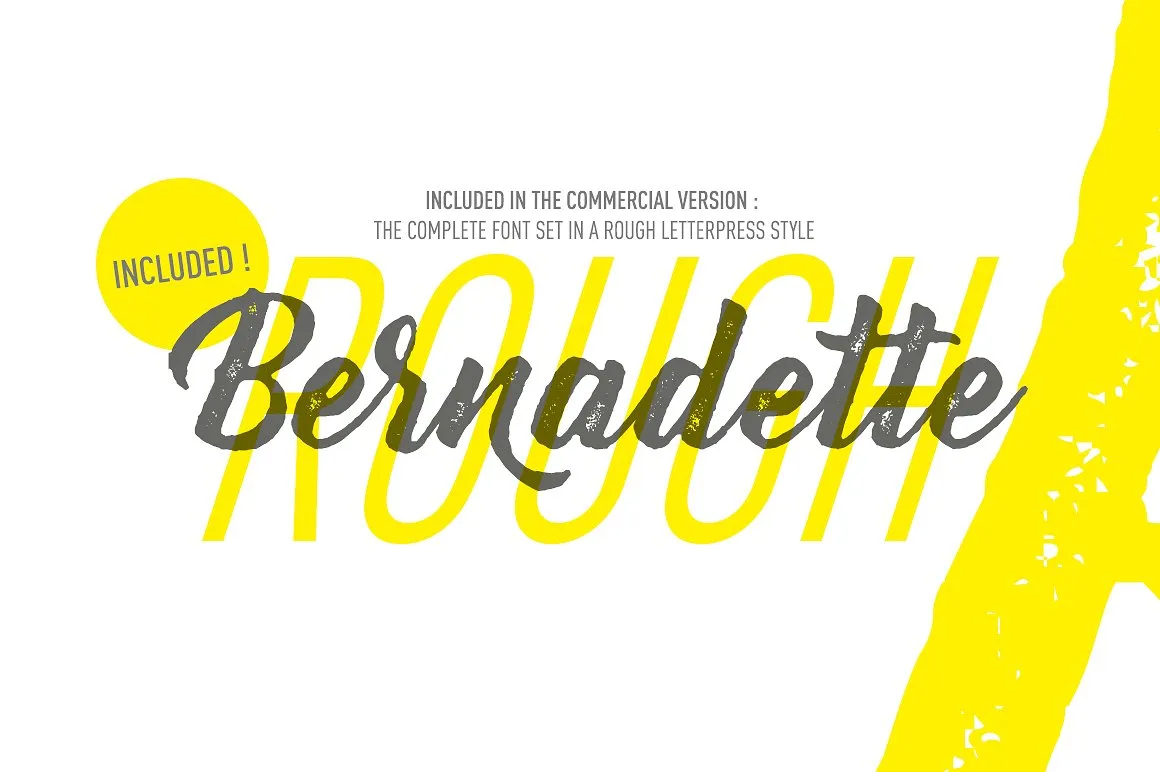
Bem-vindo ao download desta encantadora fonte chamada Bernadette. Esta fonte é exclusivamente gratuita para uso pessoal! Se você deseja obter uma licença comercial, você pode encontrá-la no site www.stereo-type.fr A versão comercial da Bernadette oferece um conjunto extenso de alternativas de glyphes e ligaturas contextualizadas, permitindo que você crie seu próprio estilo único. Você também terá a capacidade de editar arquivos PDF com fonte incorporada. A versão completa da fonte apresenta 80 alternativas de glyphes e ligaturas. Será suficiente para criar um estilo único? Eu fui apaixonado por fazer essa fonte, então espero que você também goste de usá-la!